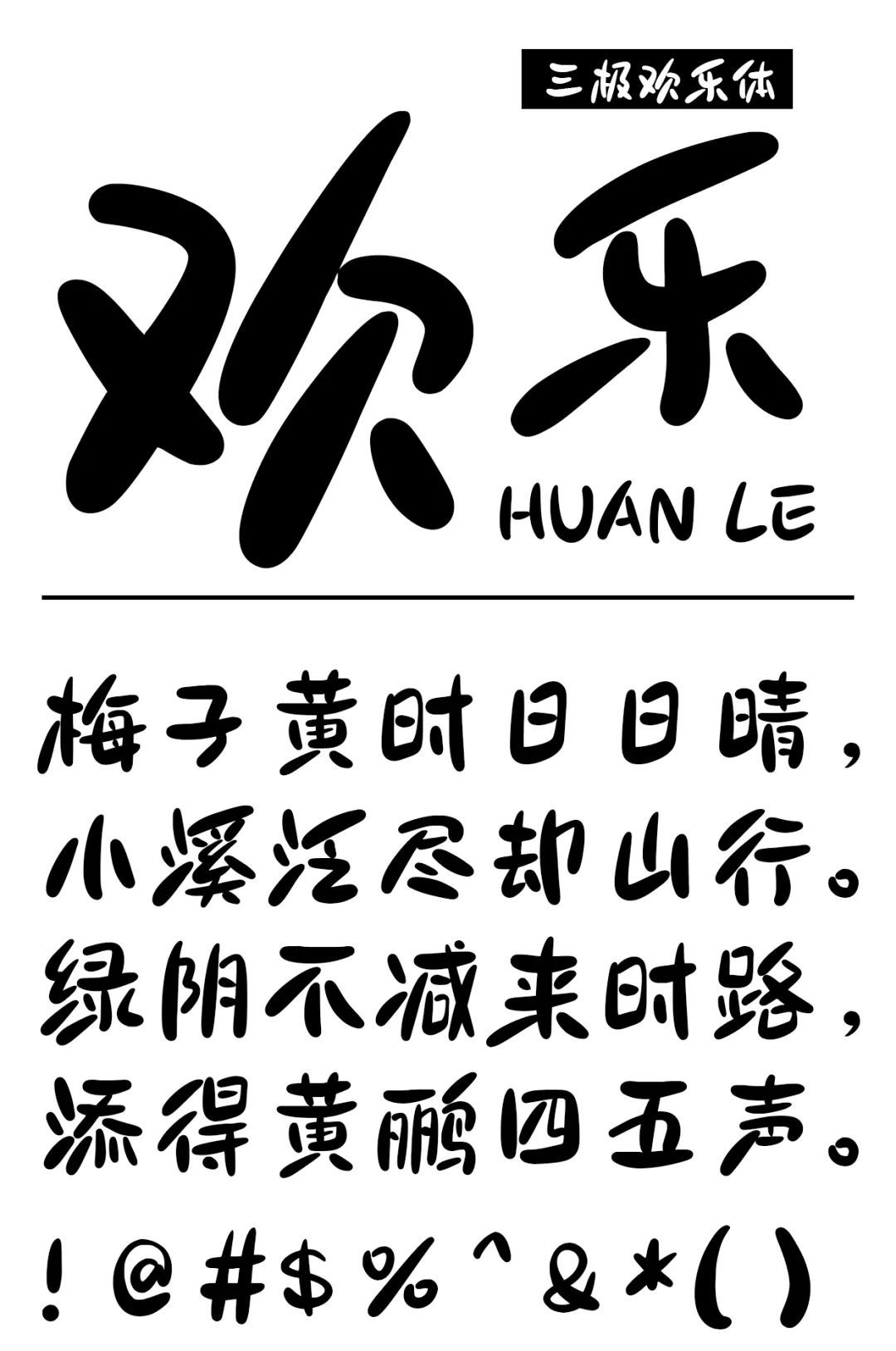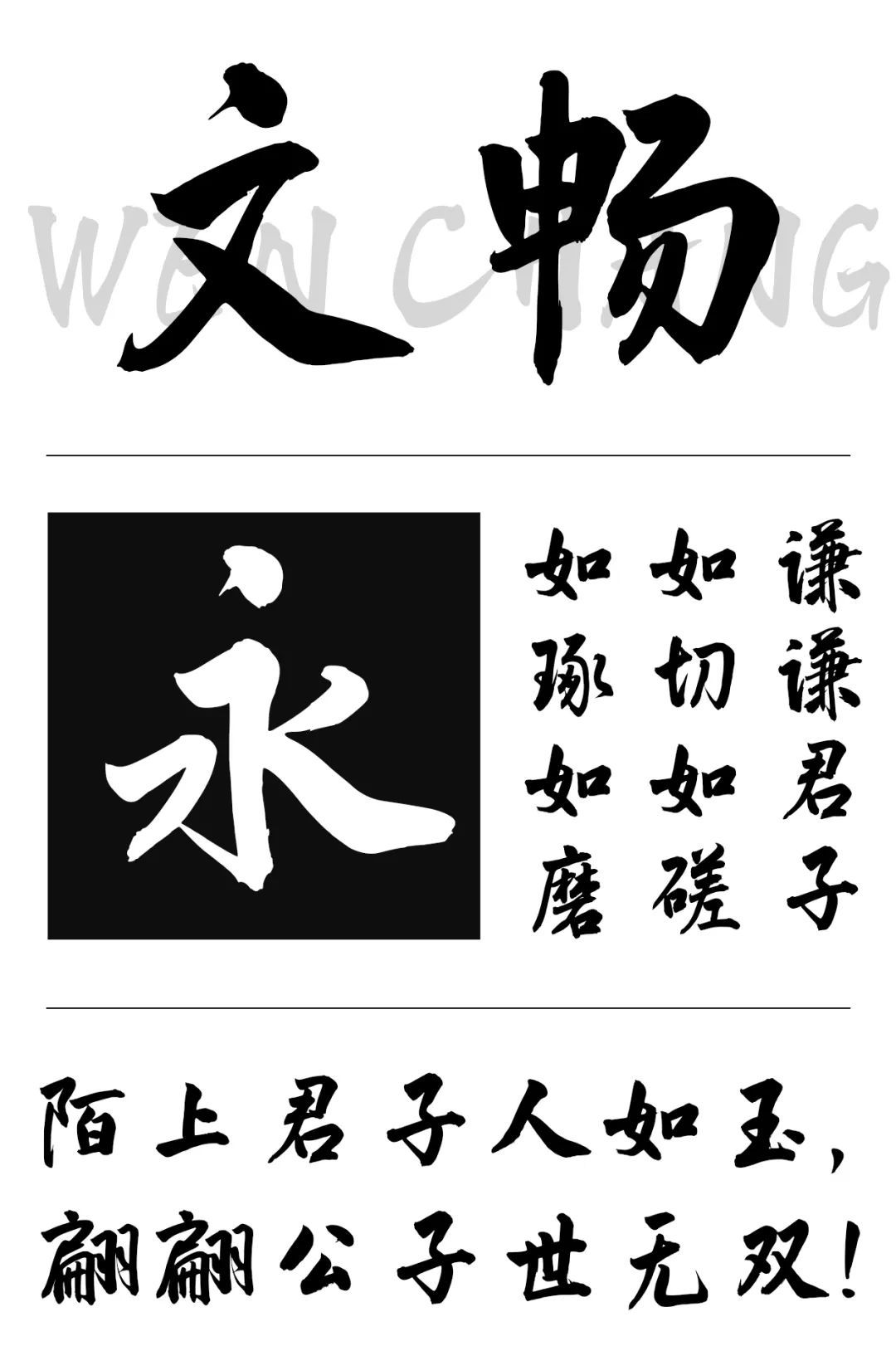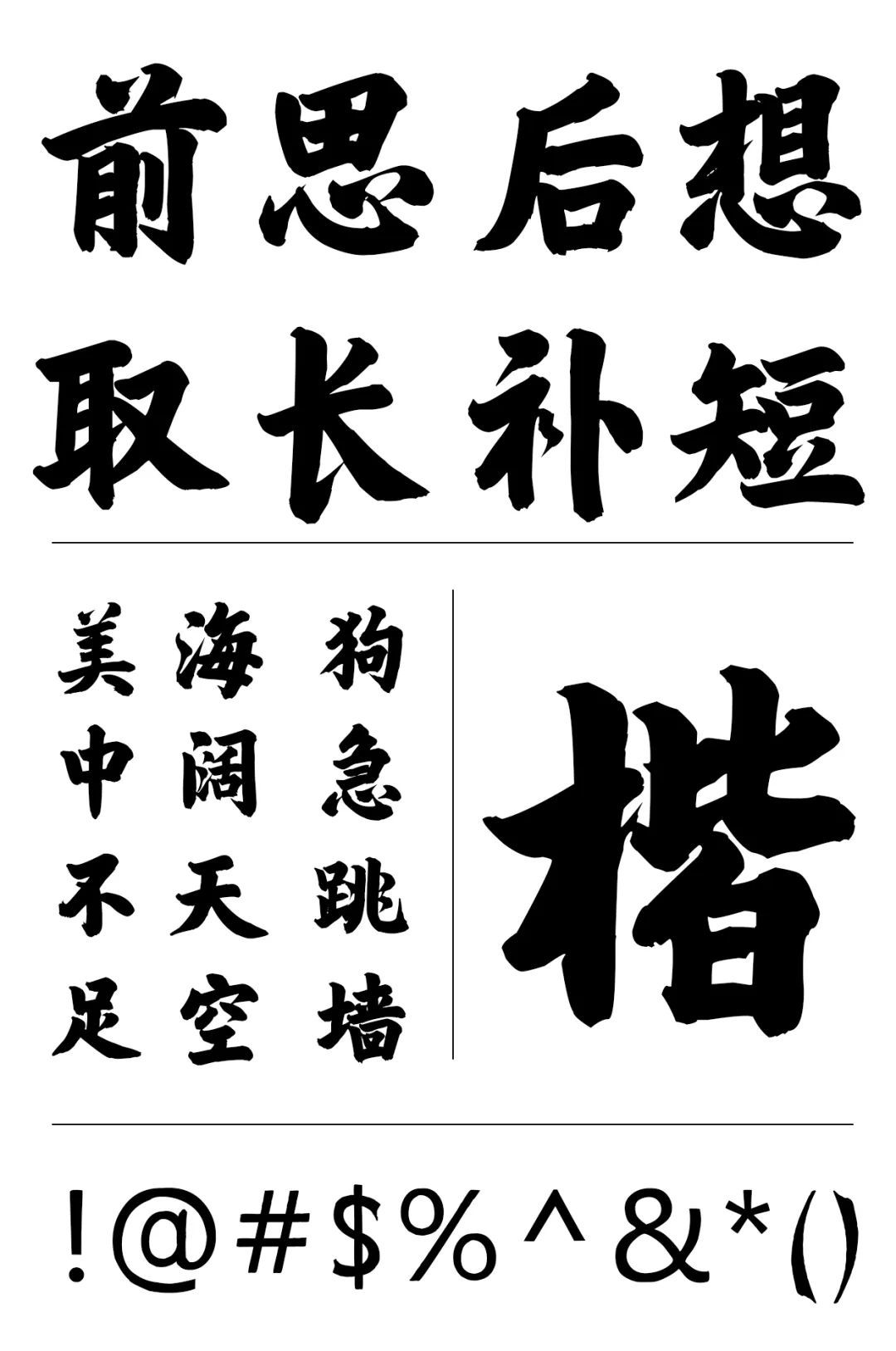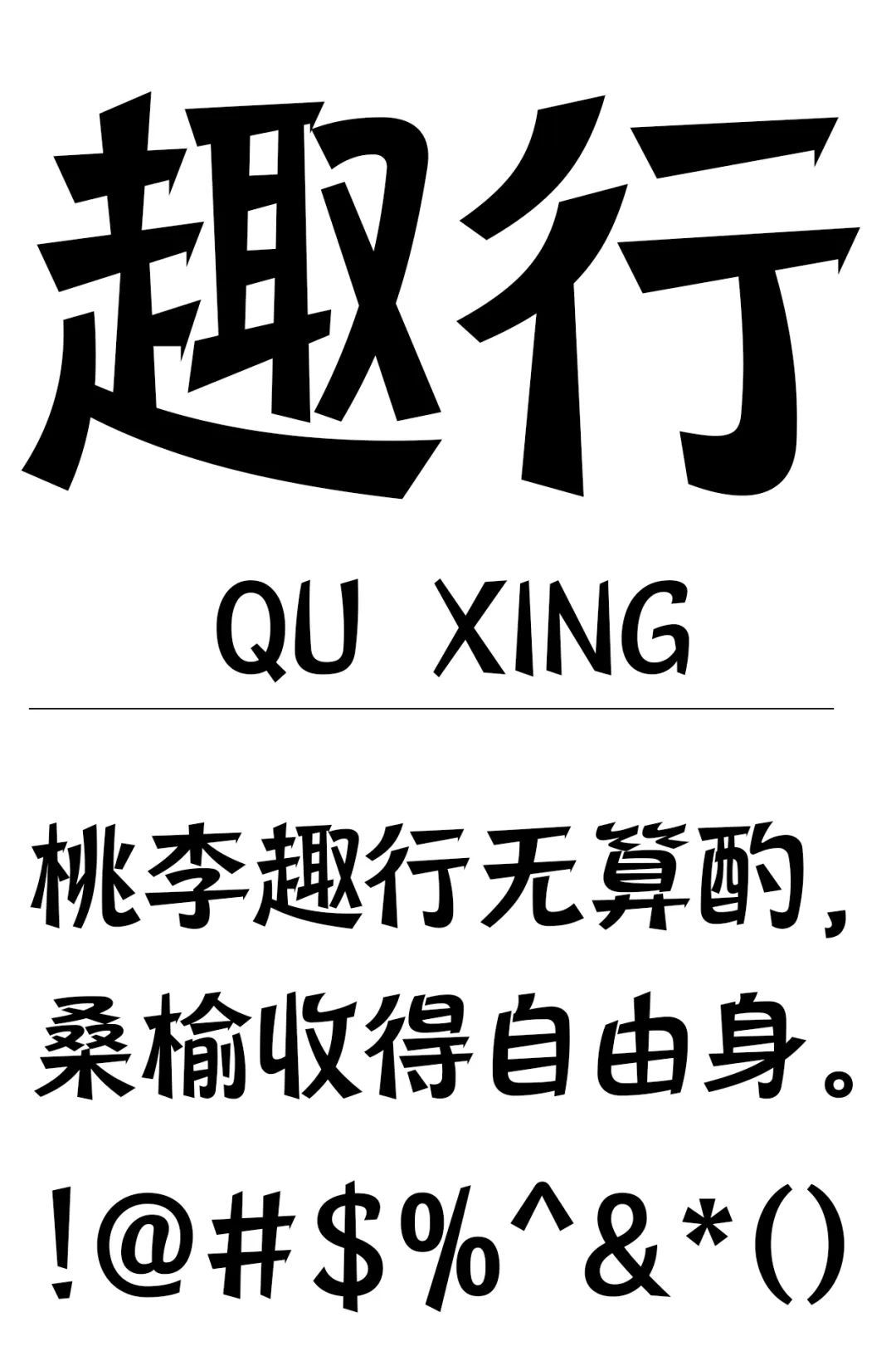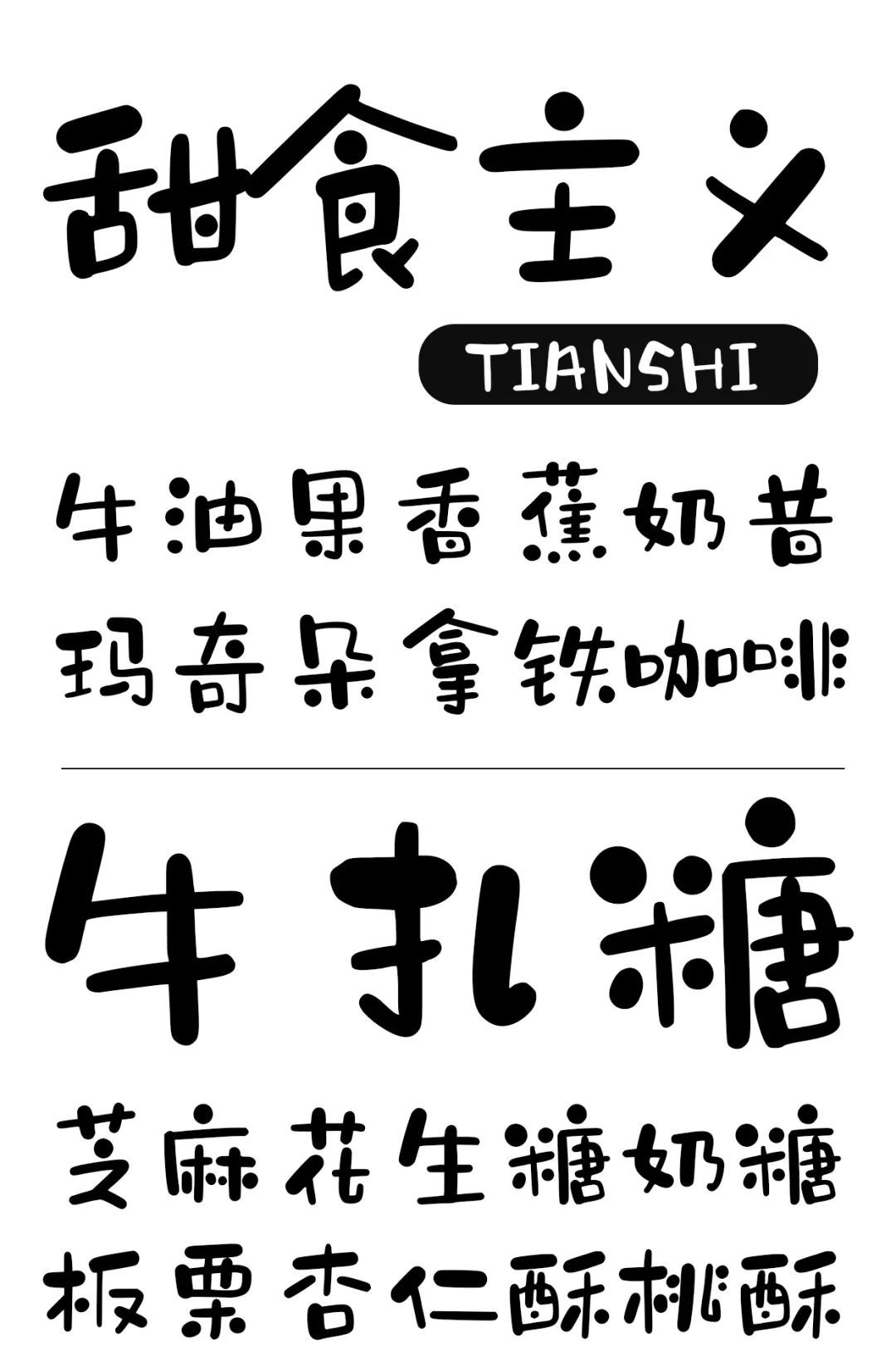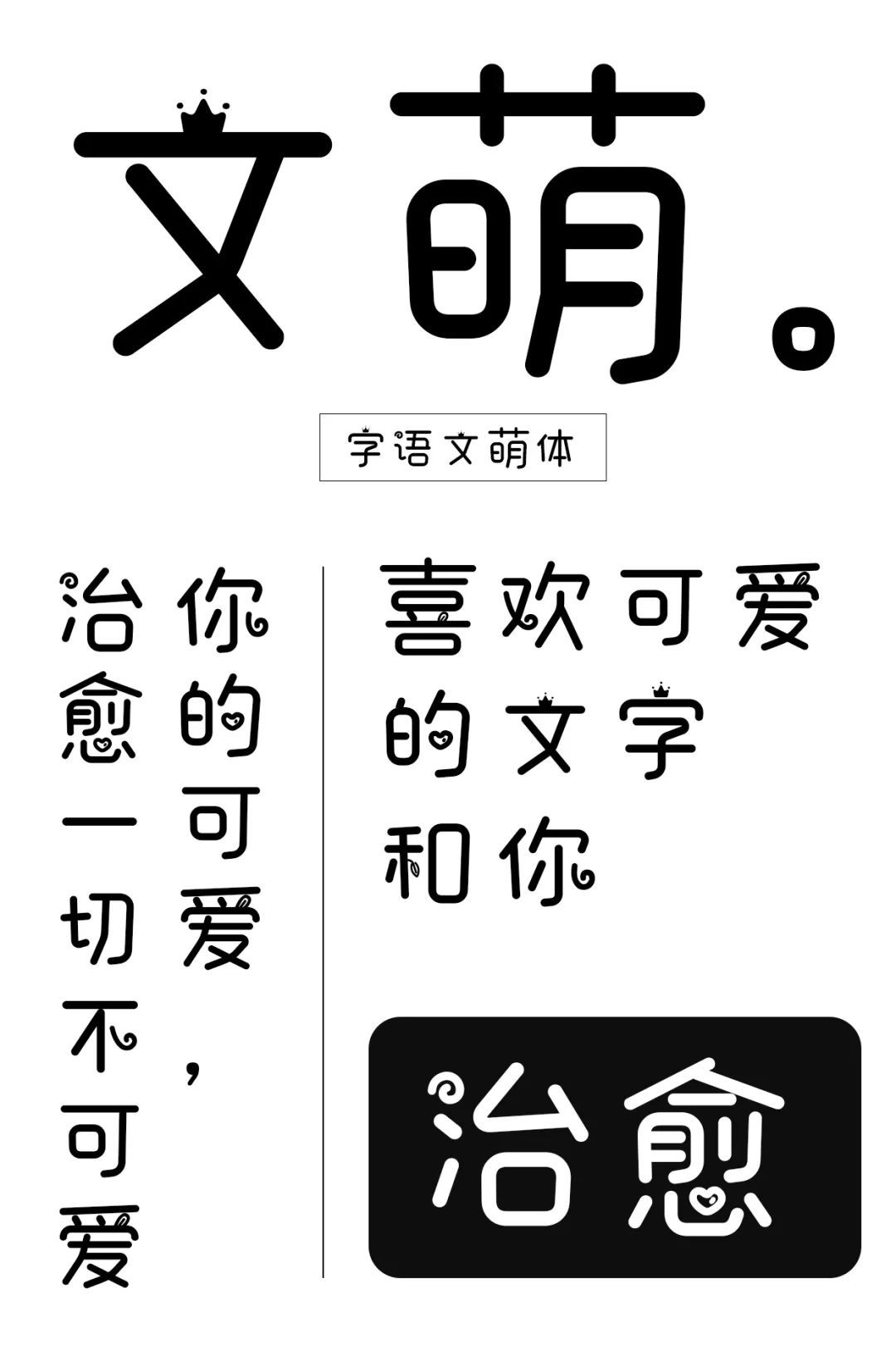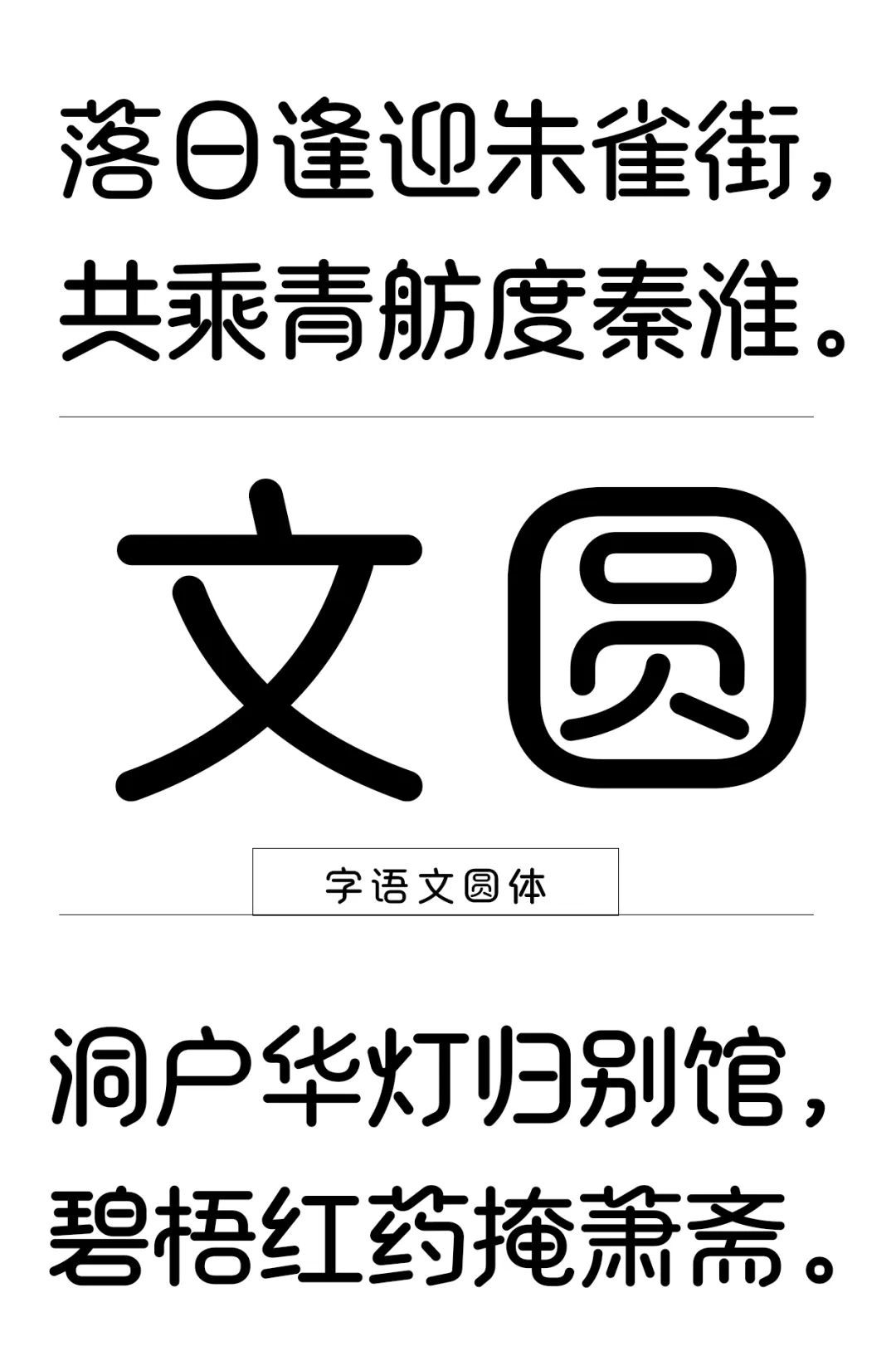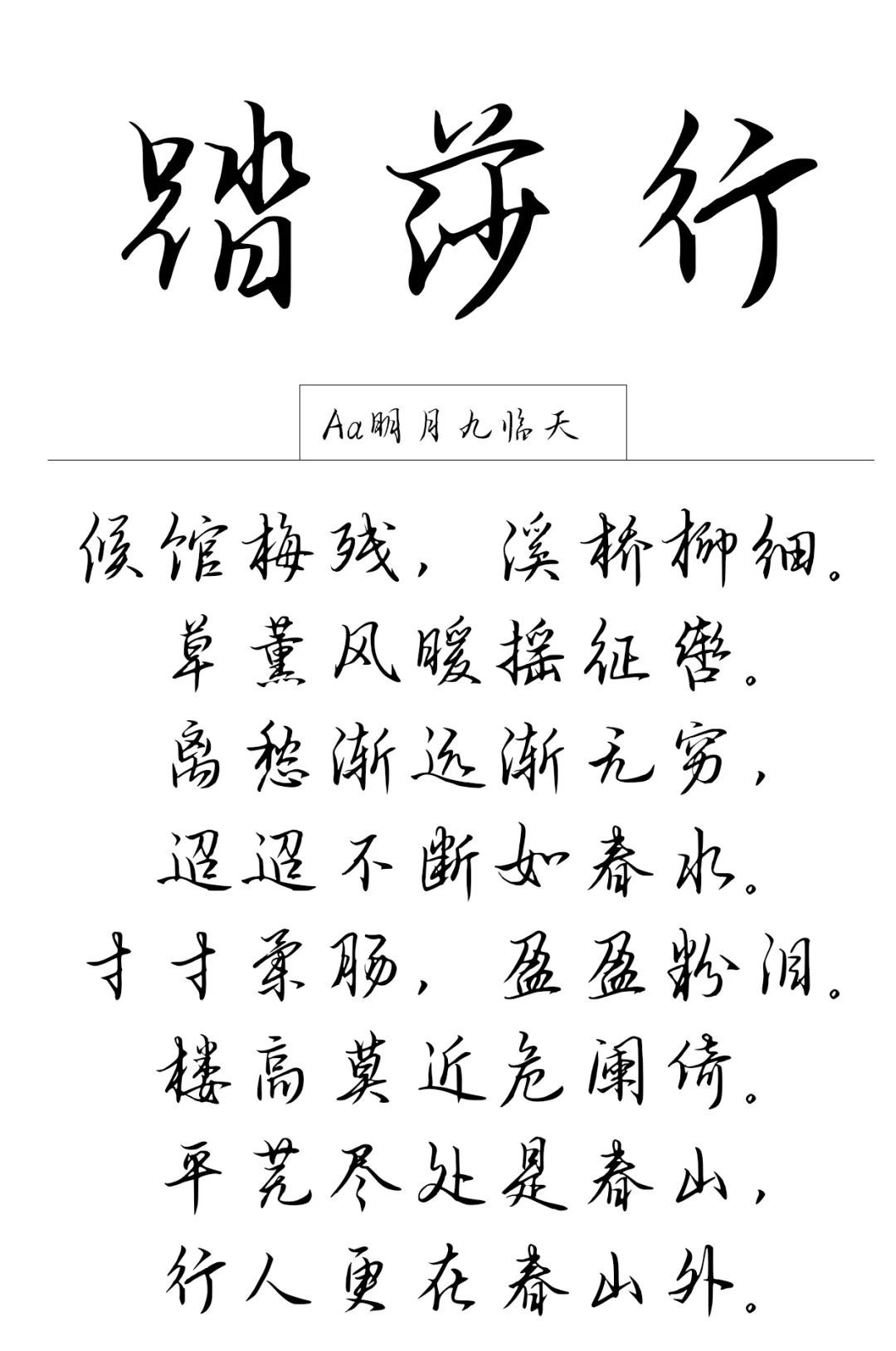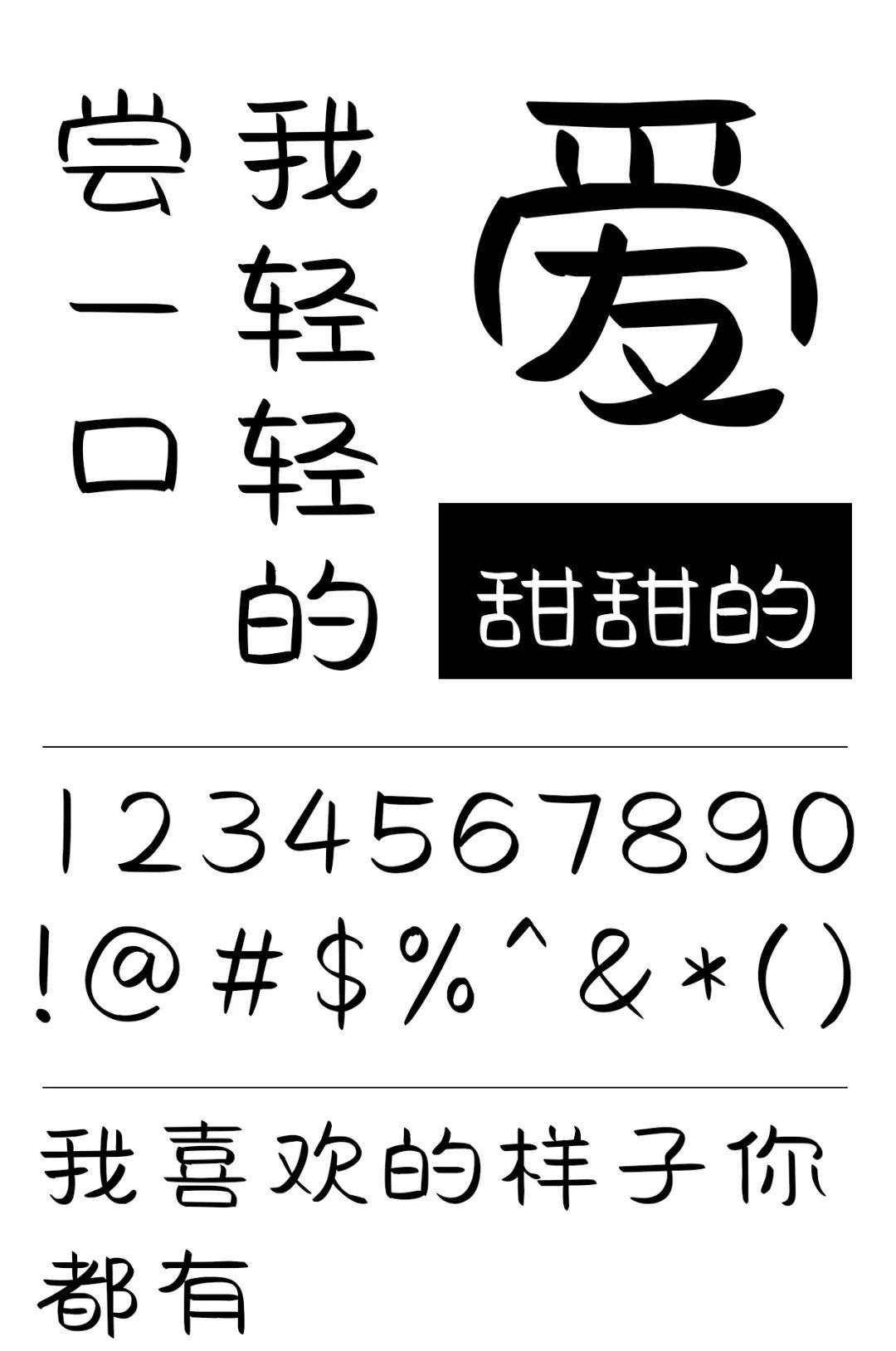
字体设计是一门重要的艺术形式,以下是本月的推荐字体,每种字体都有独特的特点和使用场景,希望能给您的设计工作带来灵感和启发。
三极欢乐体,是一款亲和力十足的创意字体。笔画圆圆鼓鼓,字形圆趣奔放,结构轻松随性,俏皮可爱的气质跃然纸上。
字语文畅体其行笔流畅自然,笔法圆熟、形意结合是一款易识性较高的书写字体。随心自在,悠然自得的风韵。
Aa凌君体通过对笔画轻重变化的统一归纳设计一款书法标题字体。
韩绍杰毛楷榜书简书法字体结合了毛笔字和楷书的特点,展现了中式书法的美感,适合用于古风作品、传统文化类的设计。
字语趣行体笔形棱角分明,风格活泼俏皮,趣味性和创意性十足。
Aa甜食主义由粗细笔画和圆点构成的一款创意字体,结构零散而出人意料,像孩子一般无拘无束、天真可爱。
字语文萌体创意字体,字体的字形结构方正但灵活活泼,意趣十足,部件融入“皇冠、兔耳朵、心、树叶、螺旋”等元素;笔画转折圆润,显得生动有趣,具有鲜明的年轻性特质。
字语文圆体字形圆润饱满,用笔简洁。整体个性萌动,轻松自在。
Aa明月九临天一款不同于传统小楷的手写字体,以美工笔书写,风格秀丽隽永。
我也想有甜甜的恋爱是一款圆润可爱手写体,每个笔画都显得柔软而可爱。